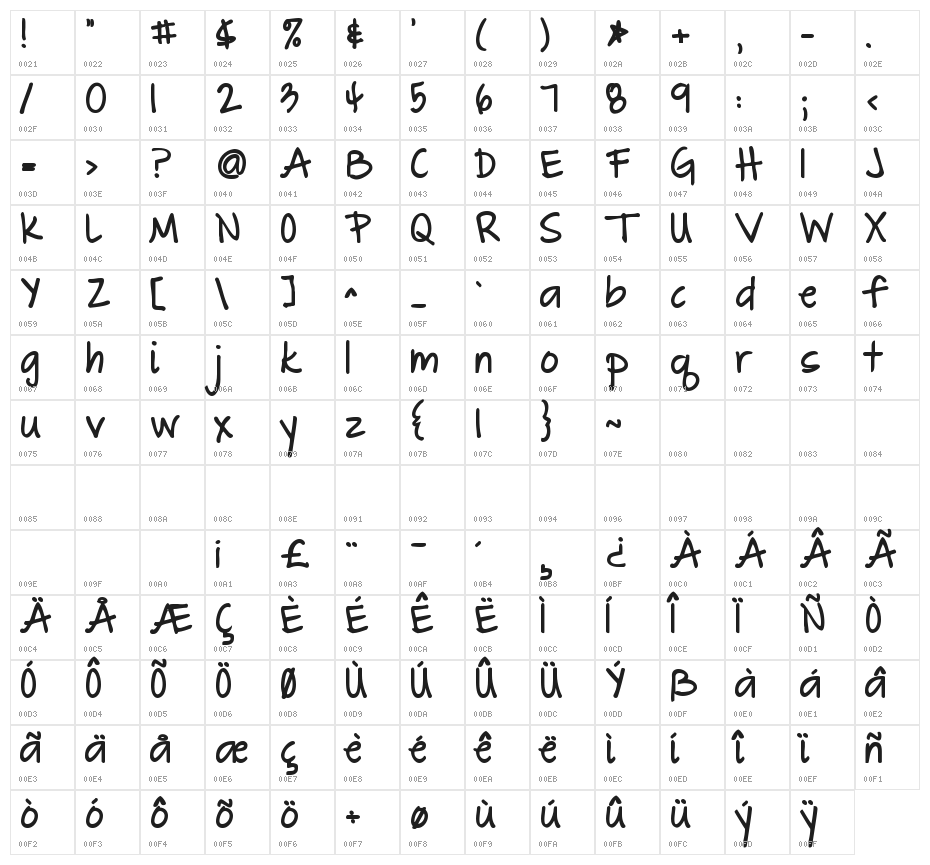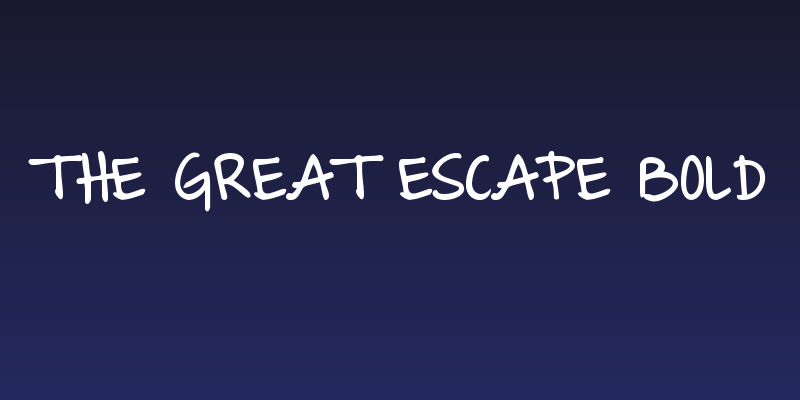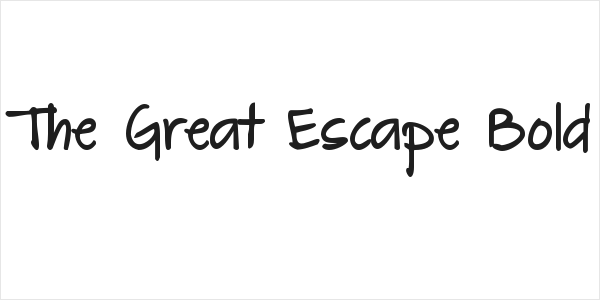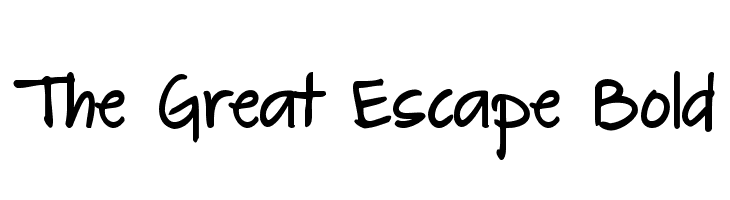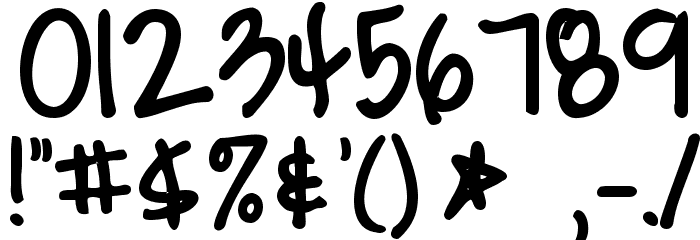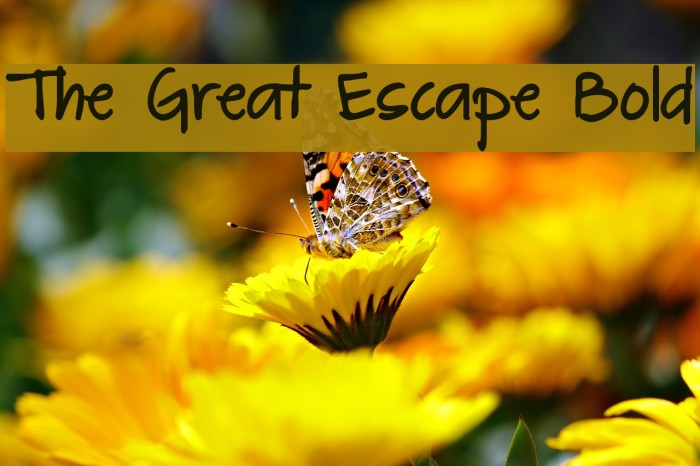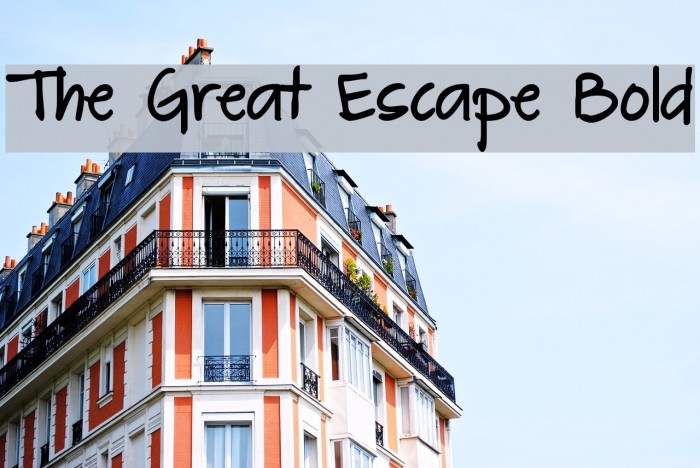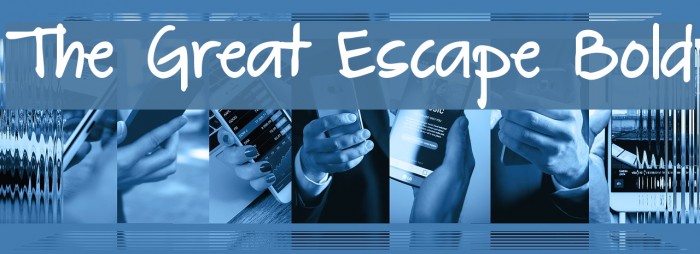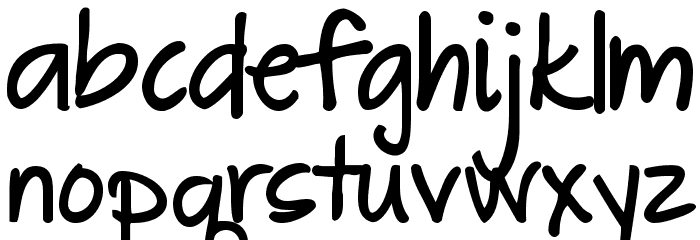
The Great Escape Bold Font
| Style général | Playful |
| Cas d'utilisation | Headlines, Logos, Informal Text |
| Projets proposés | Ideal for children's books, greeting cards, playful branding, and creative projects. |